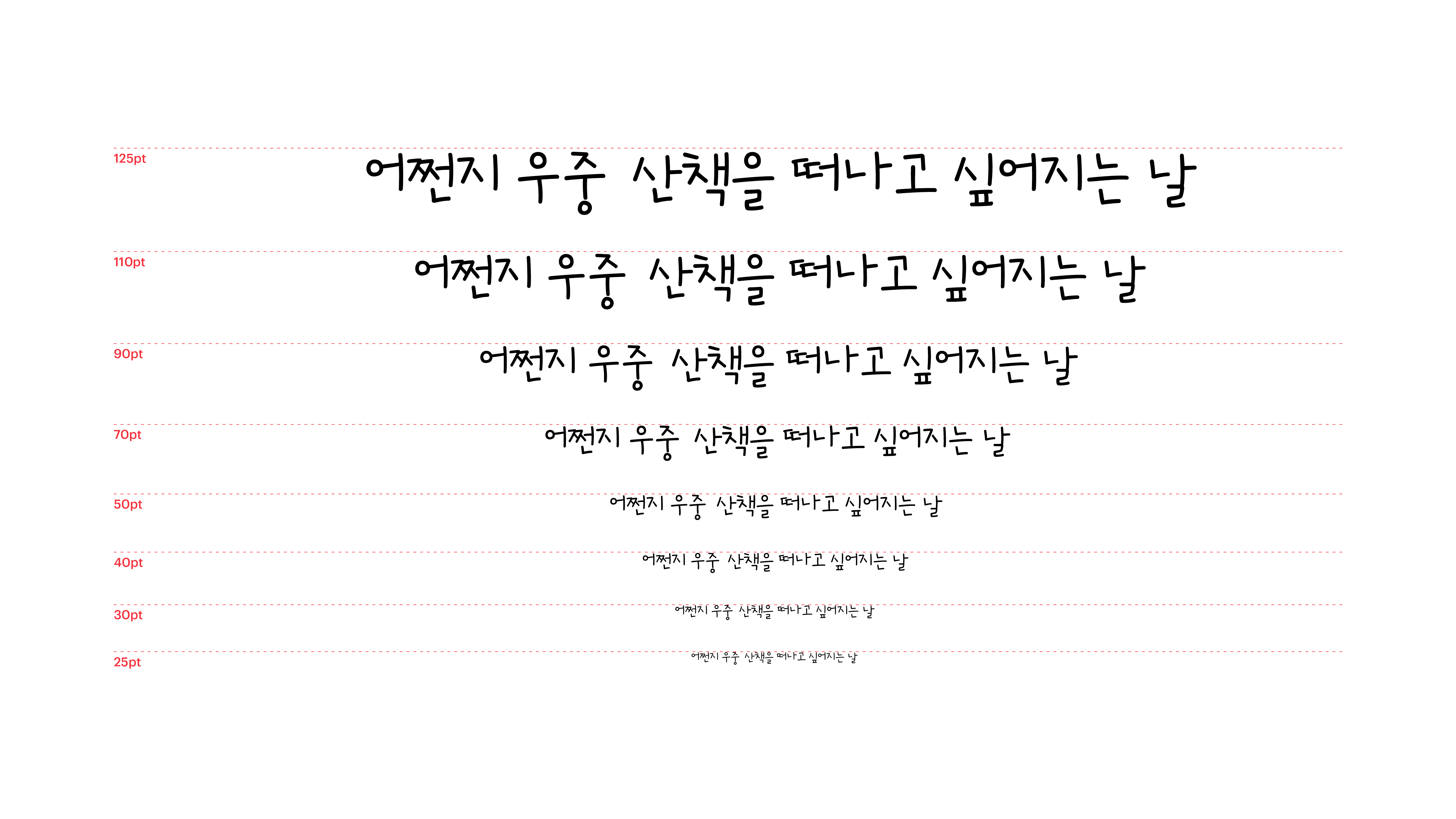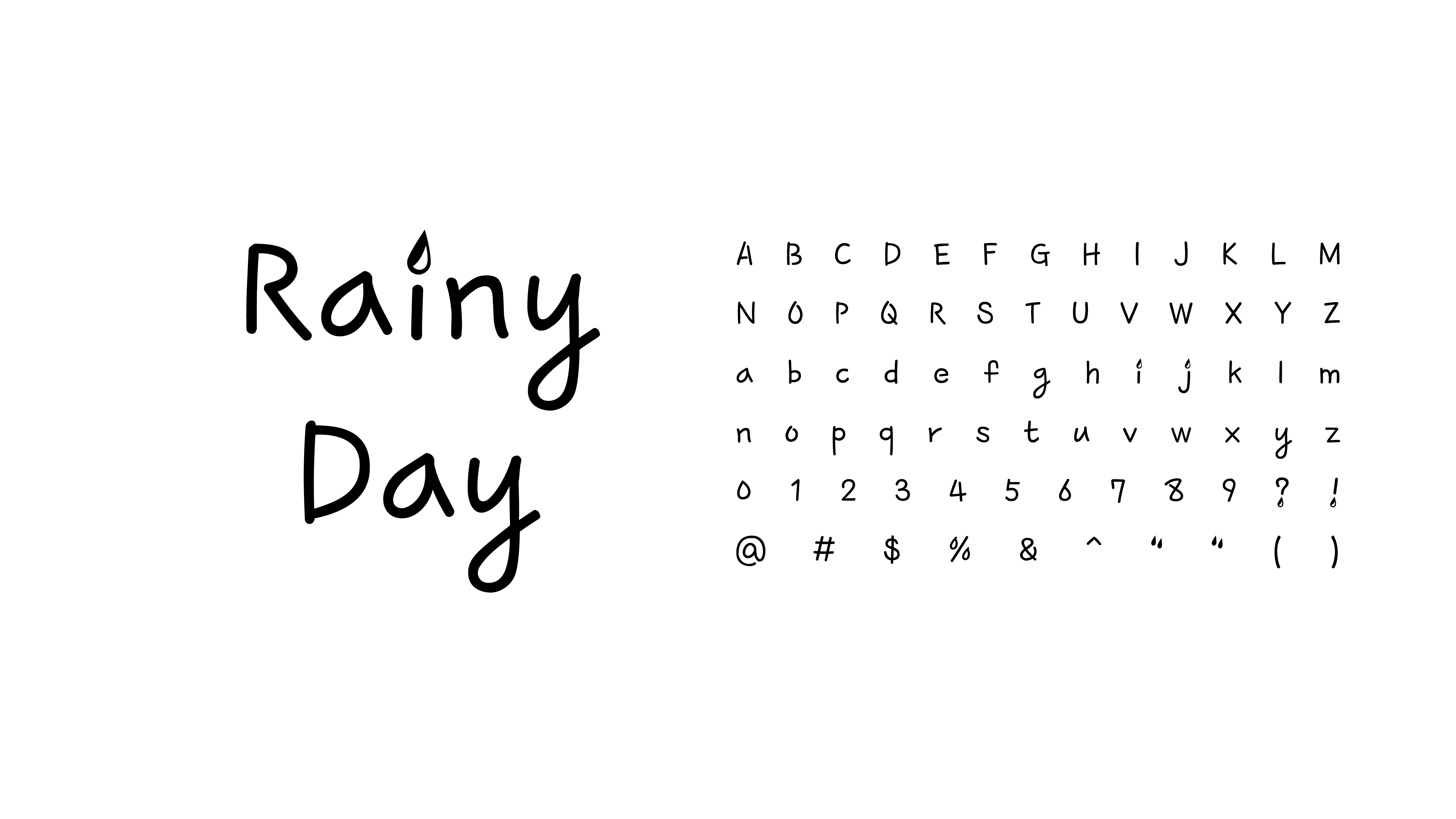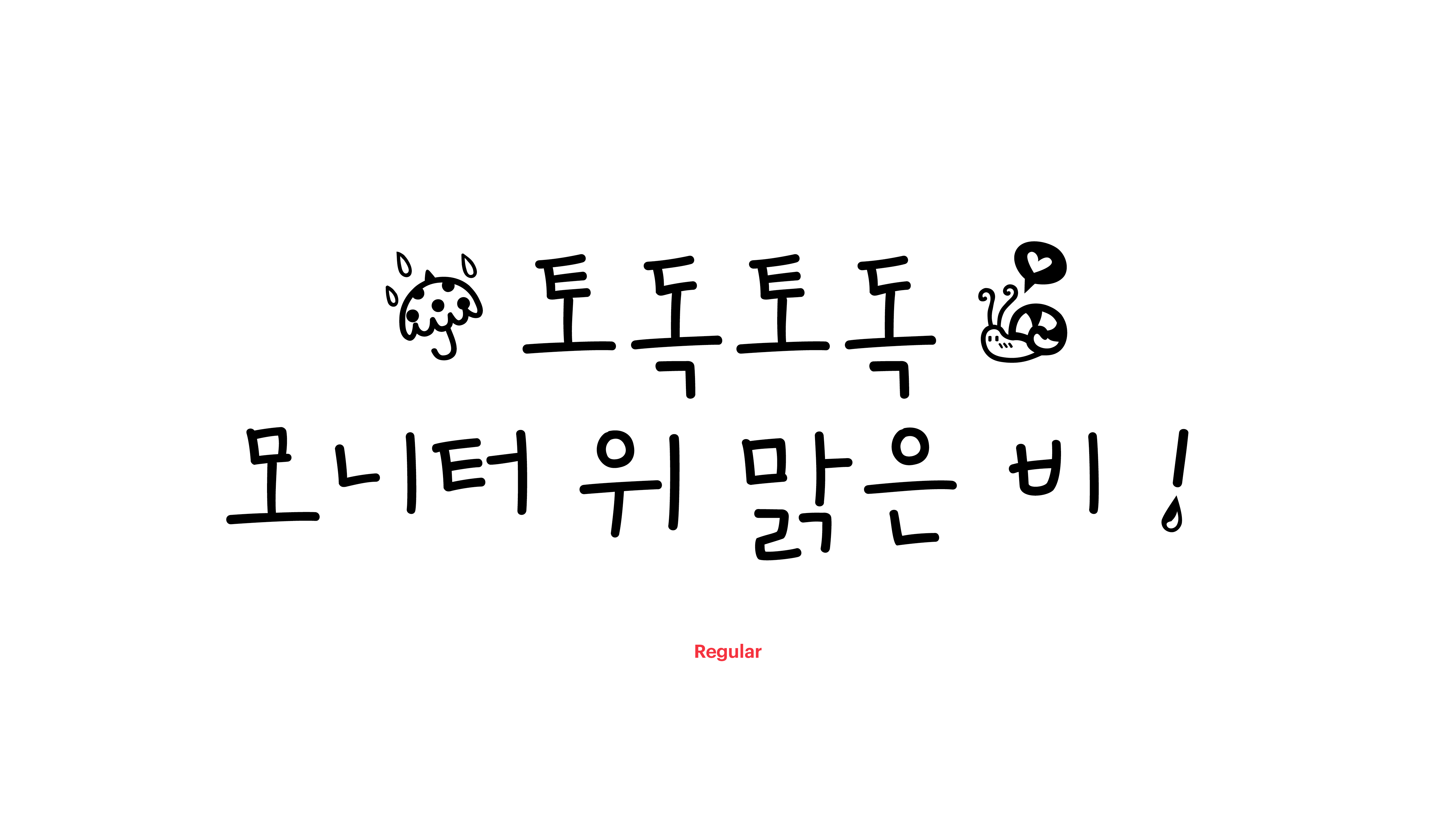
레이니데이
Yoon 레이니데이
길쭉길쭉 쏟아지는 빗줄기처럼, 시원시원한 느낌을 주는 장체 스타일의 폰트입니다. ㅇ을 조그맣고 앙증맞게 디자인해 빗방울이 그려 놓는 바닥의 동심원을 떠올릴 수 있도록 구성했어요. 어쩐지 우중 산책을 떠나고 싶어지는 날, 레이니데이체로 토독토독, 모니터 위 맑은 비를 뿌려보세요.